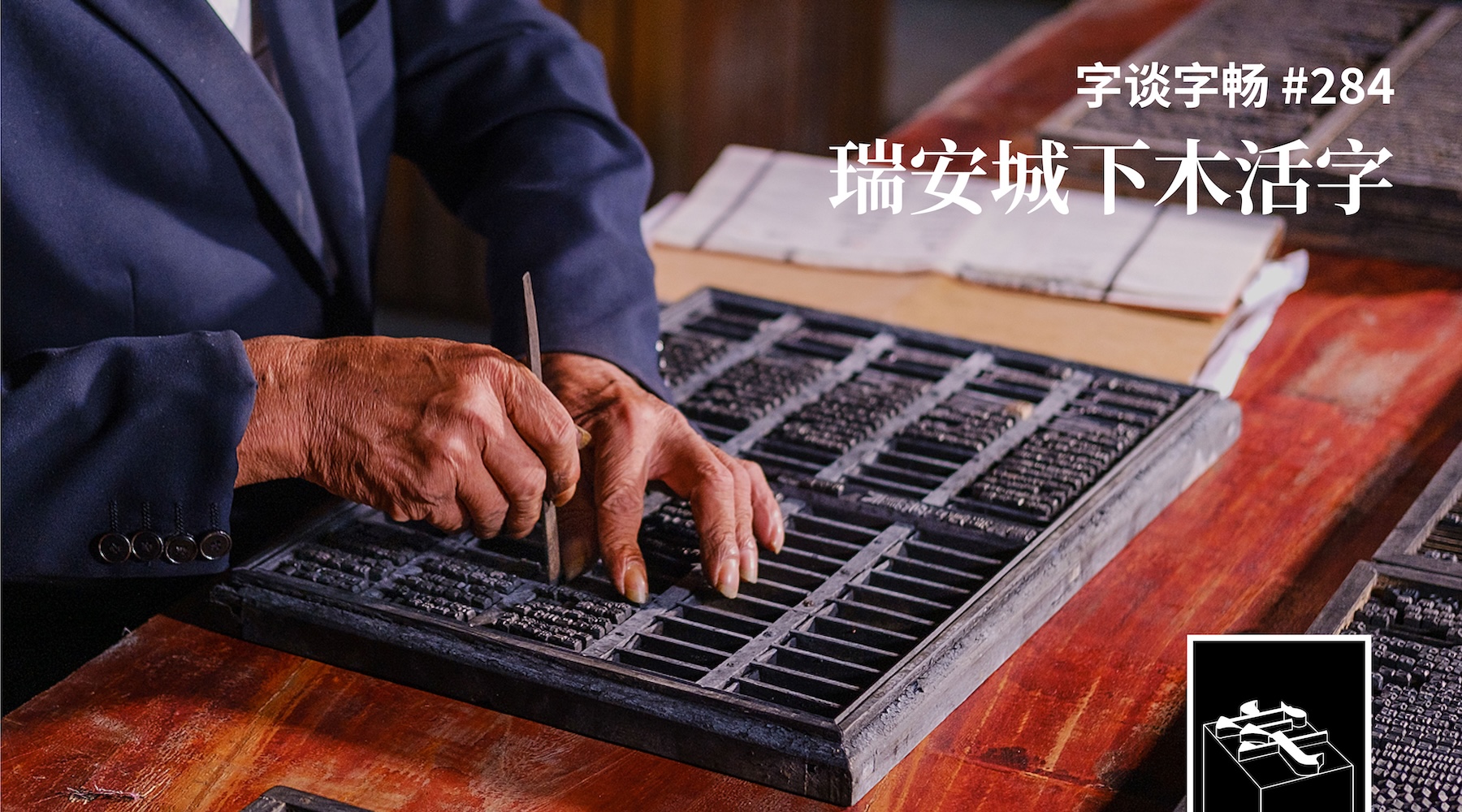
TypeChat #284
ATypI 2026 Stanford 年会如期落幕。本期节目,我们有幸邀请木活字印刷研究领域的学者吴小淮先生,为大家介绍瑞安木活字的技术细节和文化背景,以及宗谱文化与当下木活字印刷工艺传承的联系。
• 吴小淮:瑞安市木活字印刷文化研究院院长,中国非遗保护中心「中国活字印刷术」学术专员